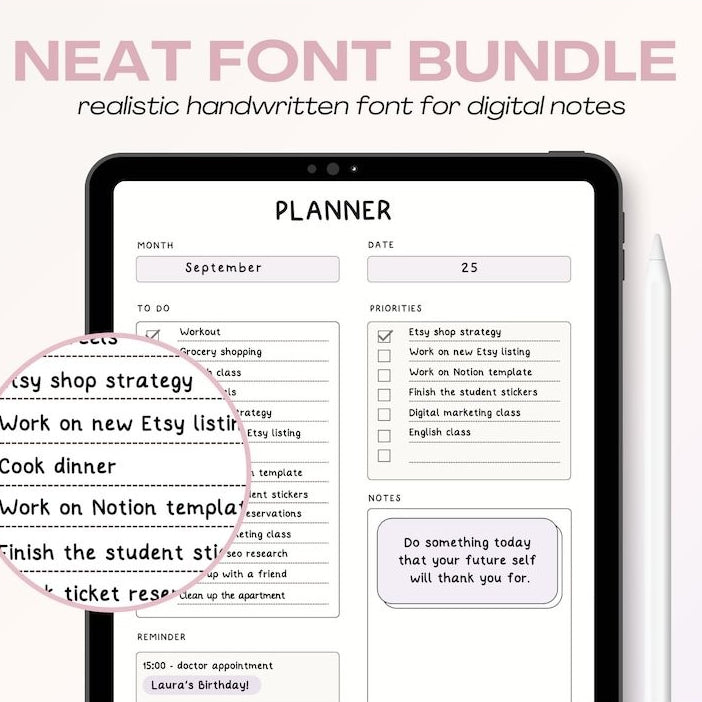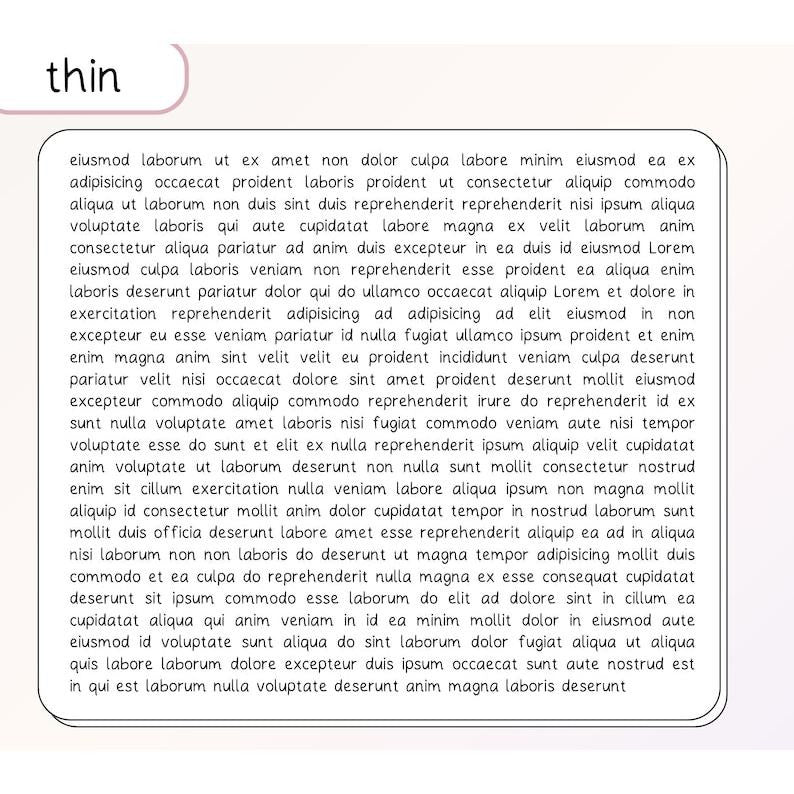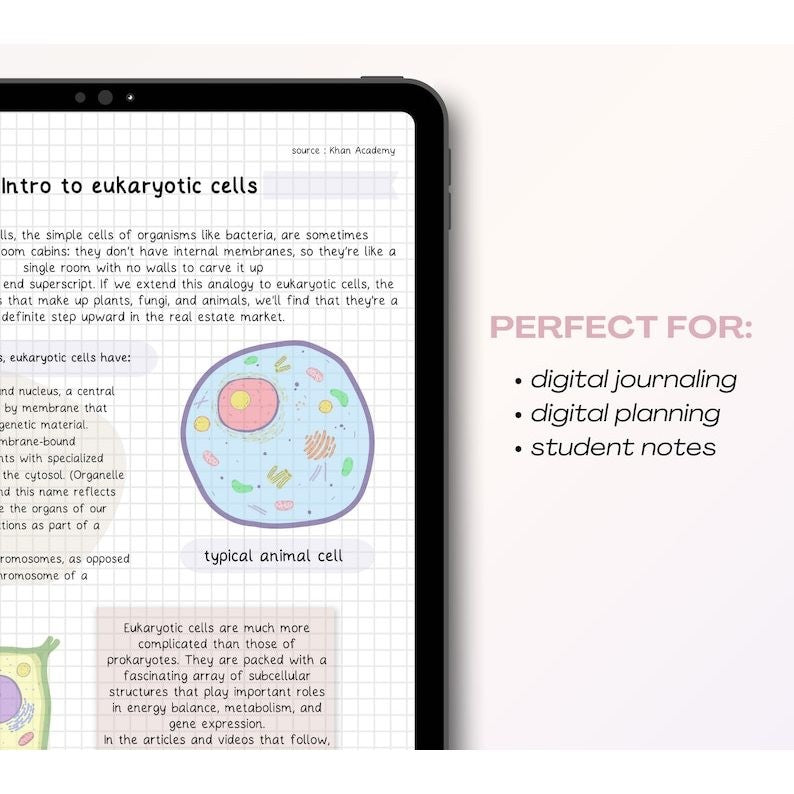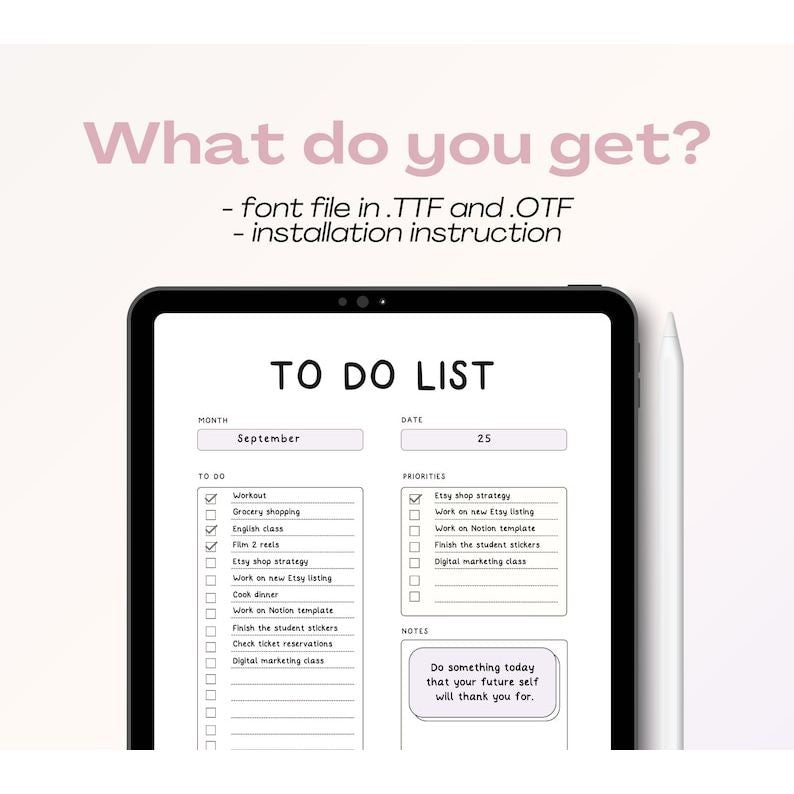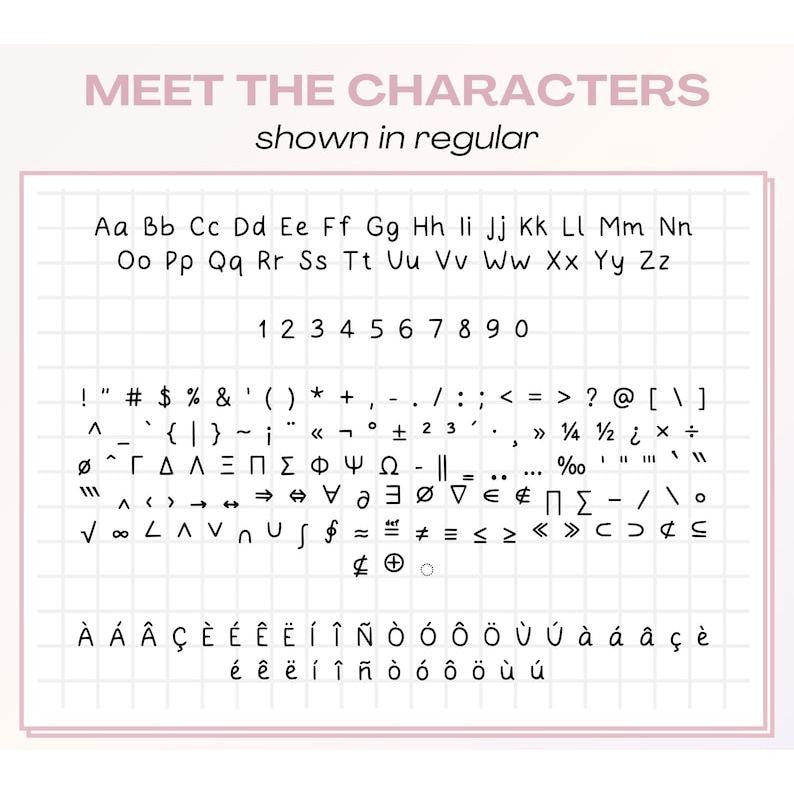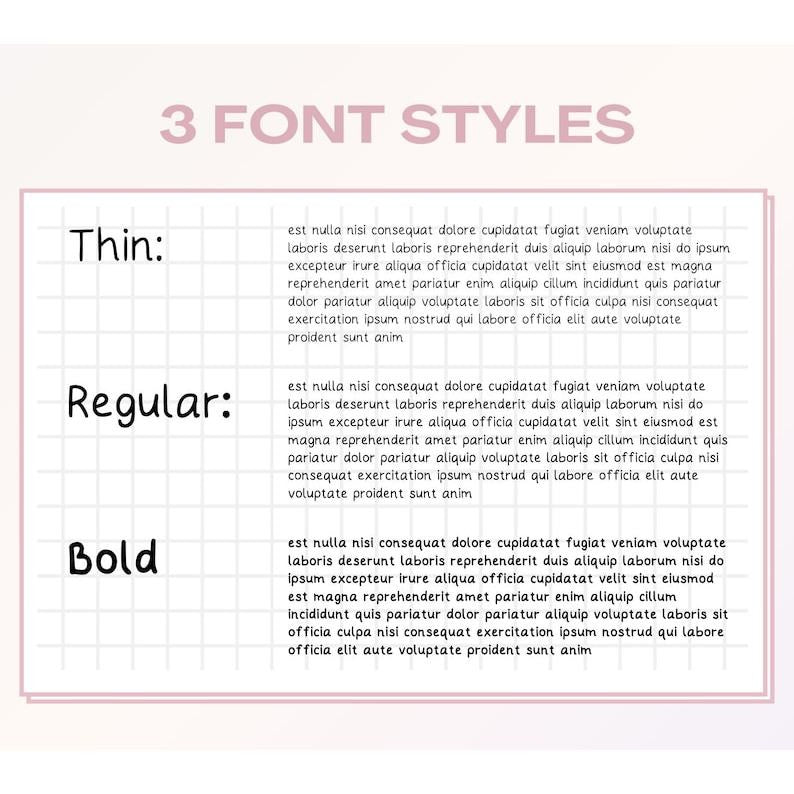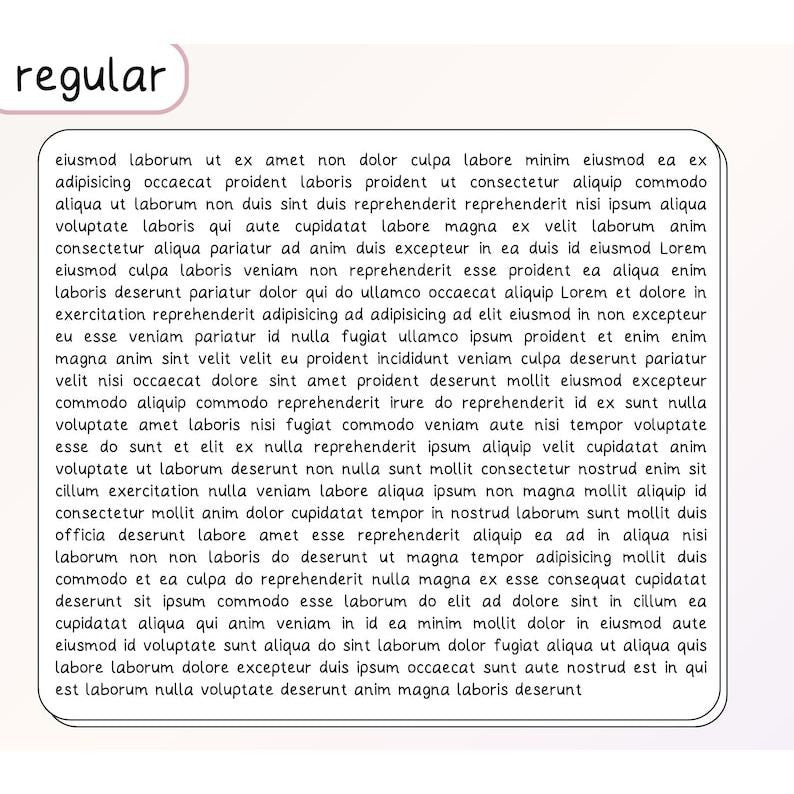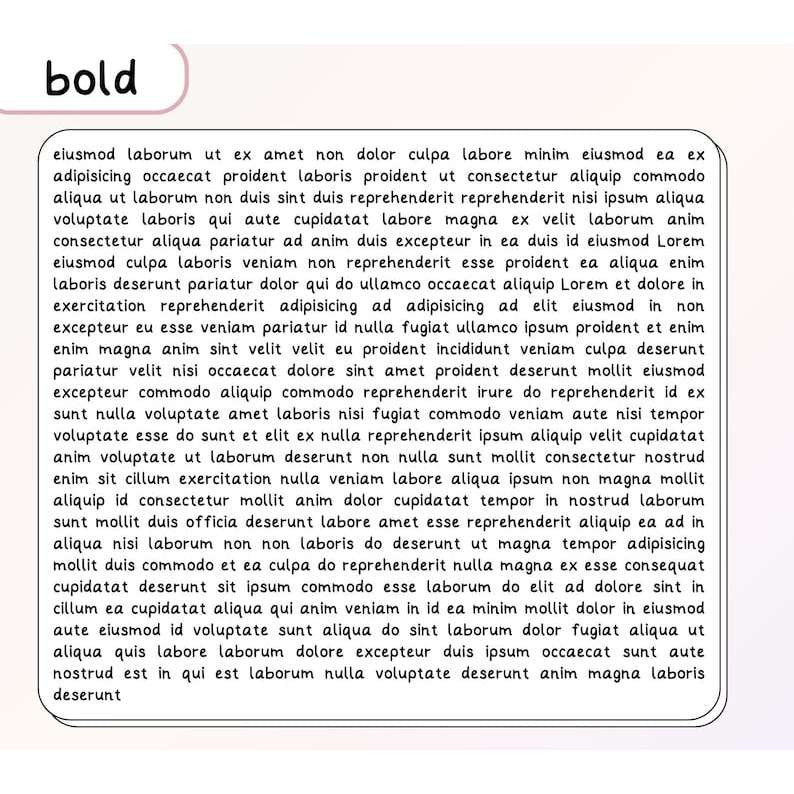
Handwritten Digital Font untuk Catatan iPad
Ingin membuat catatan digital di iPad lebih rapi dan terorganisir?
Font tulisan tangan ini cocok untuk catatan kuliah, perencanaan, maupun jurnal harian.
Font ini memiliki tampilan minimalis, realistis, dan estetik, sehingga catatan terlihat lebih bersih, tetapi tetap seperti ditulis dengan tangan sendiri.
* Thin
* Regular
* Bold
Termasuk simbol matematika dan huruf beraksen (seperti bahasa Spanyol).